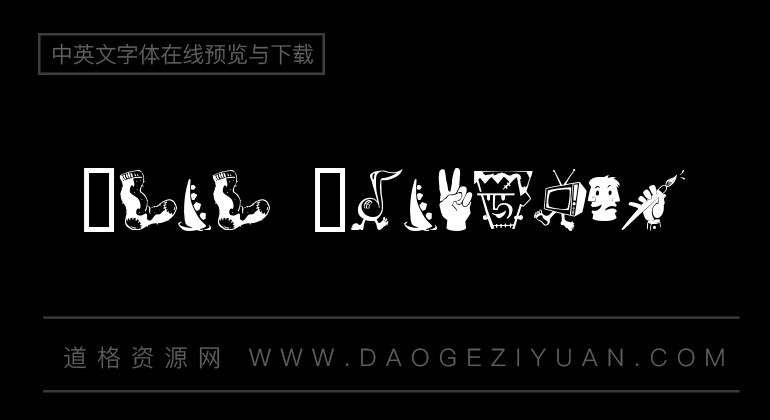
Zono Dingbats 字体是一款由日本设计师 Zono 创作的 Dingbats 字体,它由简单的符号和图形组成,可以用来制作标志、插图、图标等。它的特点是简单而强大,可以帮助您快速创建漂亮的设计。它的简洁明了的符号和图形,可以有效地传达您的设计理念,为您的作品增添一份独特的色彩。内容介绍
Zono Dingbats是一款非常不错的手写艺术字体,具有很好的视觉感,适合于文化类的宣传设计、商业类品牌的广告和产品包装设计以及个性化文字排版等较多场景。